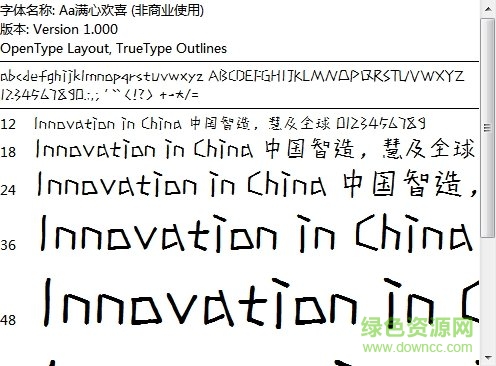
Aa滿心歡喜ttf
Aa滿心歡喜ttf是一款非商業(yè)使用的卡通字體,筆畫明朗線條清晰,讓你的閱讀擁有更加的視覺體驗(yàn),辨識(shí)性強(qiáng)文字中正醒目,來綠色資源網(wǎng)下載試試吧!
Aa滿心歡喜字體介紹
愿你我在一起的溫柔時(shí)光里
都滿心歡喜過
不辜負(fù)的相遇的運(yùn)氣
不枉費(fèi)結(jié)伴的日子